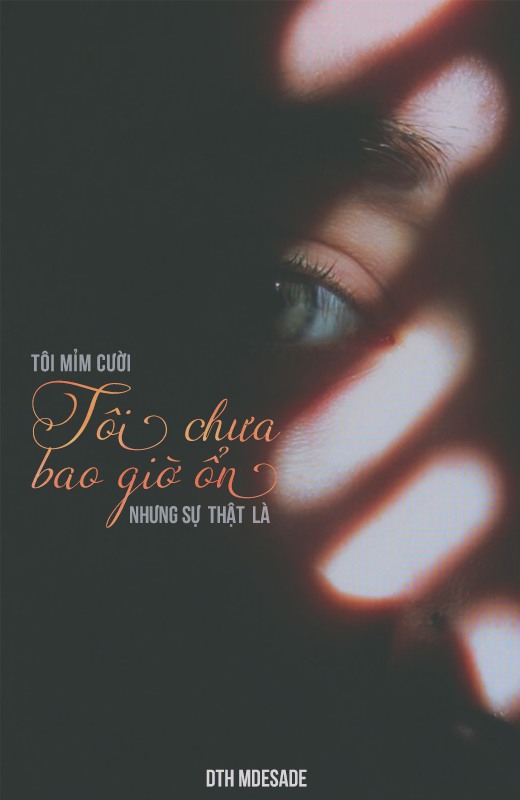
[Font] DTH MdeSade
Demo hơi xí mọi người thông cảm, font này nó bé bé xinh xinh lắm =)))) Khá là simple, mà mình thích font handwritting nên cũng ưng ưng =))))